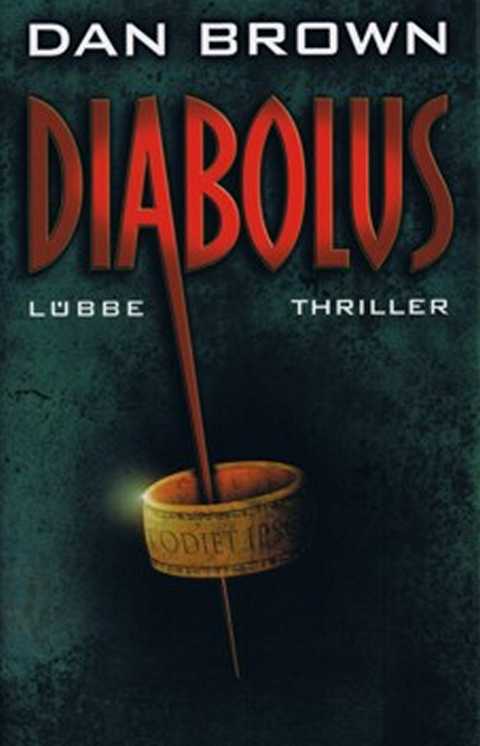
Ich suche eine passende Schrift
Ist das jetzt eher ein leichtes Kinderbuch (Der kleine Diabolus besucht die erste Jugendmesse) oder geht es eher um Sodom und Gomorrha?
es soll eine teuflische aber eher auch eine geheimnissvolle schrift sein
Das wird eine Schrift nicht leisten können. Teuflisch oder geheimnisvoll wird das Cover durch die Gesamtgestaltung, nicht durch die Schrift. Oder denkst du an solche Neger-vor-Hütte-Schriften?
Vielleicht ist dieser alte Thread ja interessant? Der ist zwar von der Ausgangsfrage her etwas anders gelagert, aber es geht auch um einen Buchtitel für ein »schauriges« Buch und es wird darauf eingegangen, wie man das in der Gestaltung angeht.  :-)
Die Diavlo ist aber eher niedlich denn teuflisch …